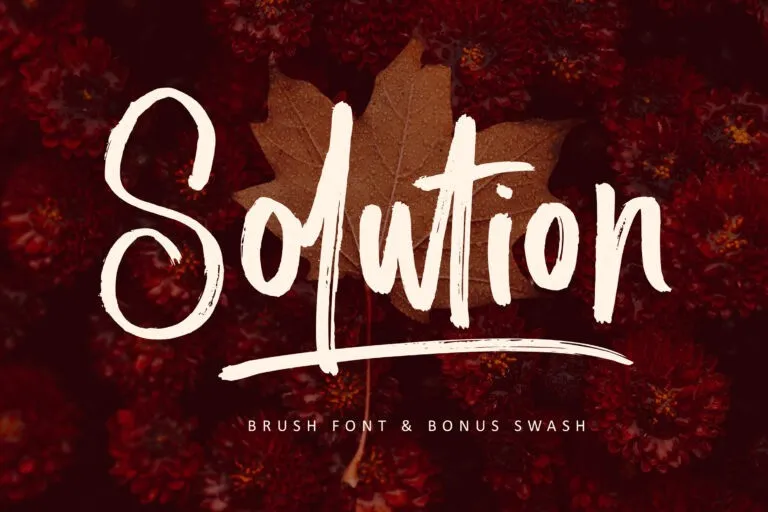
Solution Brush Font – Download Grátis
A Solution Brush Font é uma tipografia criada por Fontherapy, que representa uma script aquarela feito à mão. Especialmente projetado para headlines, logotipos e assinaturas, essa font oferece um estilo urbano e moderno. Perfeita para adicionar um toque único em trabalhos de design como panfletas, logomarcas ou anúncios. Com sua elegância fluida e personalidade marcante, a Solution Brush Font é ideal para aqueles que buscam uma cara única para seus projetos visuais. Não importa o contexto ou formato do seu projeto, essa font pode transformá-lo em algo ainda mais poderoso e inovador. Engane-se, não apenas mudará sua forma de escrever, mas também a maneira como visualiza as coisas.